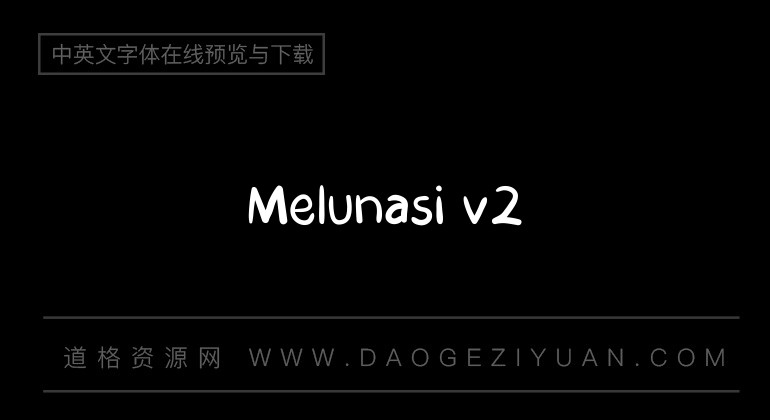
Melunasi v2 是一种现代化的无衬线字体,由设计师 Riffki Fauzi 创建。该字体拥有流畅、圆润的特点,同时也带有一些角度和锐利的边缘,使得字体看起来既柔和又有力量。Melunasi v2 字体的字形清晰,易于阅读,适用于多种设计和排版场景,如海报、广告、书籍、标志等。此外,该字体也拥有多种字重和字形变体,可适应不同的设计需求。内容介绍
Melunasi v2是一款非常不错的手写艺术字体,具有很好的视觉感,适合于文化类的宣传设计、商业类品牌的广告和产品包装设计以及个性化文字排版等较多场景。